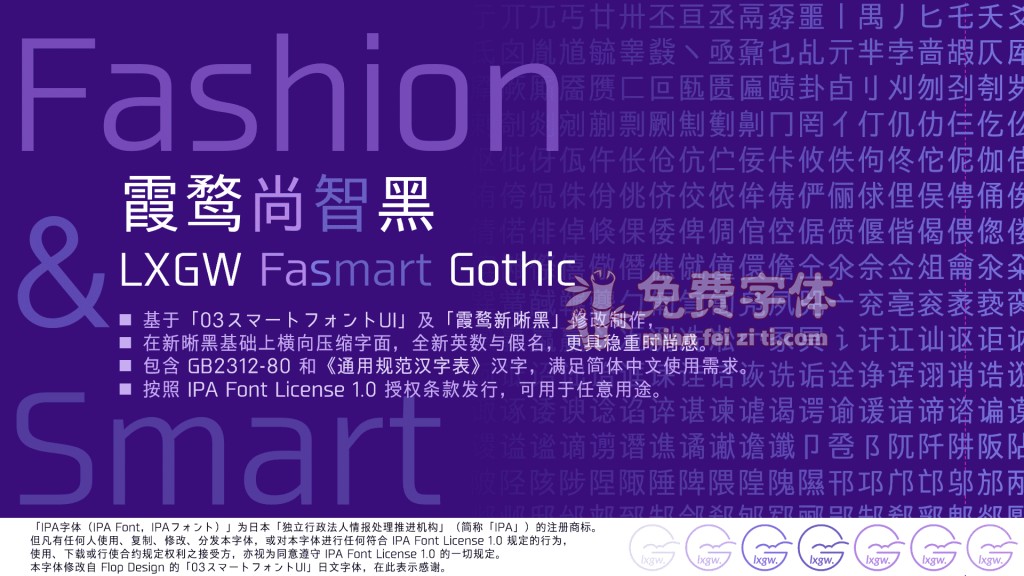
霞鹜尚智黑是一款衍生于03智能字体UI的及霞鹜新晰黑的简体中文黑体字型。03智能字体UI是一款基于IPAex黑体的中文开源字体。霞鹜尚智黑在新晰黑的基础上横向压缩字面,全新英数与假名,更具稳重时尚感。
霞鹜尚智黑增补中国大陆的简体字形,包含GB2312-80和《通用规范字表》汉字,使其更加适合中国大陆用户的需求。按照IPA Font License 1.0授权条款发行,可用于任意用途。